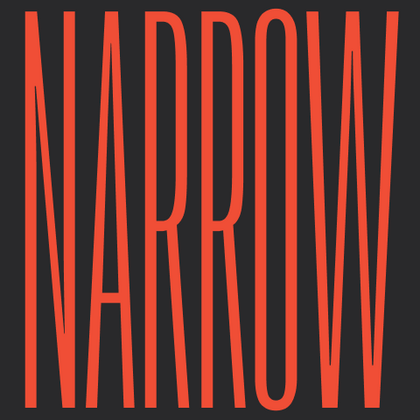
Узкий шрифт
Узкие шрифты — это гарнитуры с компактными пропорциями, где каждый символ оптимизирован для экономии пространства без потери читаемости. Их вертикально-ориентированный дизайн особенно востребован в интерфейсах, таблицах и рекламных материалах с ограниченной площадью. В коллекции TypeType представлены как ультраконденсированные варианты для заголовков, так и умеренно узкие решения для основного текста — все они сохраняют баланс между плотностью и удобочитаемостью.
TT Nooks Serif — акцидентная новостильная антиква с лёгким налётом эгоцентричности. У неё острый и твёрдый, при этом элегантный и статный характер.
TT Chocolates — изящный гуманистический гротеск сo сбалансированными пропорциями, близкими к классическим. Шрифт с приятным дружелюбным характером, который интуитивно воспринимается как что-то знакомое.
TT Nooks Script — шрифт с уникальным рисунком, который не имеет прямых аналогов.
TT Qurdisma — узкий и плотный декоративный шрифт, напоминающий причудливое растение. Вьющиеся, плавные контуры рождают растительный орнамент.
TT Supermolot Neue — технологичный модульный гротеск с футуристическим настроением и мощным функционалом. Яркость его характера сочетается с универсальностью применения.
В TT Frantz можно найти небольшие отсылки в эстетике арт-деко, которые выражены в сильно заниженной или наоборот сильно завышенной талии у букв. Кроме того, в зависимости от положения ползунка регулировки оси, у некоторых букв изменяется закрытость апертуры.
TT Moons — узкая и контрастная антиква. Данное шрифтовое семейство очень элегантно работает в классических темах дизайна. TT Moons по стилистике относится к глиптальным новостильным шрифтам. Идеальная сфера использования TT Moons — это верстка журналов, книг и газет.
TT Disruptors — дуктальный рукописный шрифт, созданный с помощью маркера. Его рисунок уникален: потёртости, неравномерная толщина штрихов и удлинённые выносные элементы придают ему живую, динамичную текстуру и ощущение рукотворности. Характер этого шрифта своенравный и эмоциональный, но при этом тёплый и душевный.
TT Interphases Pro — неогротеск, который создавался специально для работы в интерфейсах. Среди визуальных особенностей TT Interphases Pro — плавные формы скруглений, повторяющиеся во всех элементах: благодаря им большие массивы текста читаются легко и приятно.
TT Drugs — ленточная антиква: это шрифт без засечек, но с выраженным контрастом.
TT Biersal — акцидентный гротеск со свободным, озорным и авантюрным характером. Отправной точкой для его создания послужил немецкий плакат начала 30-х годов. Мы хотели сохранить не только пропорции, но и ощущение небрежности, живости леттеринга из референса.
TT Cometus — современная брусковая антиква. Название гарнитуры отсылает к образу кометы — мощного увесистого тела с красивым хвостом, грациозно рассекающего космические просторы с огромной скоростью.
TT Octosquares — октагональный гротеск с футуристическим характером. Этот шрифт отличается геометричностью и своеобразной «мозаичностью»: он как бы собран из отдельных фрагментов, что проявляется и в мельчайших деталях.
TT Carvist — современный экспериментальный гротеск со сверхузкими пропорциями. Название гарнитуры отсылает к резьбе по камню: характерные черты этого шрифта — геометричность и брутальность.
TT Ricks — выразительная антиква с острым характером. Создавая ее, мы вдохновлялись шрифтом De Vinne, разработанным Густавом Шредером в 1892 году. Это «злая» антиква, которая, впрочем, иногда усмиряет свой дерзкий нрав.
TT Espina — дисплейная антиква с выразительными засечками. При ее создании дизайнеры вдохновлялись исторической формой буквы «O», которая приобретала ромбовидную форму из-за качества печати. В каждую букву хочется всматриваться, так что заголовки, оформленные TT Espina, точно привлекут внимание.
TT Lakes Neue в версии 2.0 — продолжение геометрического гротеска, вдохновлённого финским функционализмом. Новая версия предоставляет больше возможностей, ведь мы не только увеличили кассовый состав и улучшили шрифт технически, но и доработали его визуальный характер.
TT Rounds Neue — гротеск со скругленными формами. В тонких начертаниях шрифт выглядит довольно минималистично и нейтрально: скругленные окончания штрихов становятся практически незаметными, на первый план выходят плавные линии.
TT Trailers — стильный и выразительный акцидентный гротеск. Его легко узнать по необычной графике: рисунок каждого знака в этом шрифте авторский, формы экспериментальные. Он гармонично смотрится в оформлении афиш и плакатов, идеально подходит для оформления титров. Однако на практике сфера применения этой гарнитуры гораздо шире.